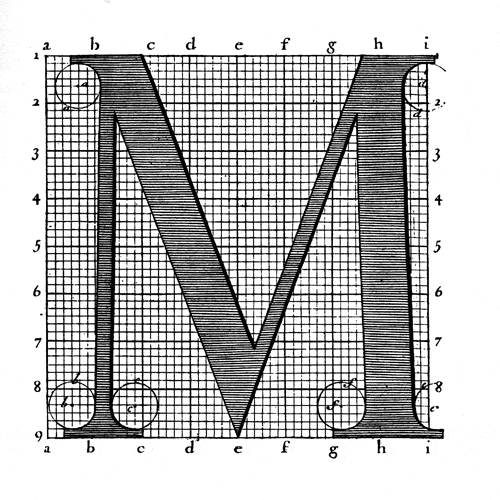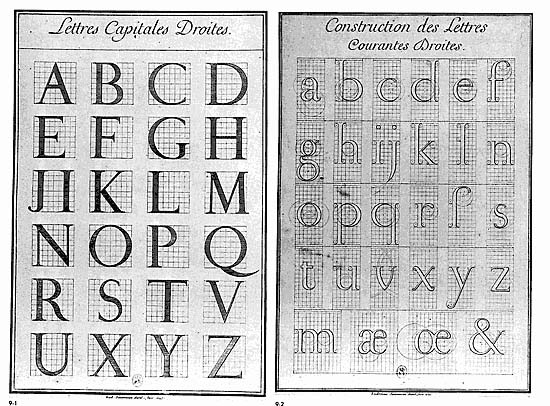
Grandjean / Roman du Roi
Os caracteres gravados por Grandjean romperam com a tradição dos caracteres criados por Jenson e Garamond e abriram caminho à construção de caracteres muito diferentes, nomeadamente aos criados por Didot e Bodoni, em que existe um contraste muito mais acentuado entre as hastes grossas e finas.
Grandjean
O Grandjean ou Romain du roi, do qual foram gravados 21 corpos entre 1693 et 1745. Foi o único tipo usado na 'Imprimerie Royale até 1811.
No século XVI, em plena Renascença, a melhor tipografia europeia vinha de França, mas já no fim do século a herança de Claude Garamond e Jannon entrou em declínio.
Para ressuscitar o esplendor francês, foi fundada em 1640 a 'Imprimerie Royale por decreto real.
No reinado do monarca absolutista Louis XIV, uma comissão real composta por dez especialistas investigou e debateu a partir do ano de 1692, até finalmente aprovar um tipo totalmente novo: o de Philippe Grandjean – em 1702.
Foram precisos dez longos anos para aprovar estes novos caracteres, baseados em conceitos matemáticos, construidos sobre uma grelha ortogonal. Este Grandjean, o «mais belo de todos os tipos», já não tinha qualquer afinidade com os padrões caligráficos que haviam cunhado as garaldes.
Depois de aprovado, o Grandjean passou a chamar-se Romain du Roi. Mas como o tipo era propriedade exclusiva da Imprimerie Royale, todas as outras fundições tiveram de fabricar os seus próprios tipos – o que acabou por favorecer a concorrência estrangeira.
Jean Anisson, director da Imprimerie Royale, tinha decidido renovar a Typographie royale. Tomou parte nas sessões da Commission Jaugeon, encarregada de definir o desenho dos caracteres.
Para executá-los, recorreu a Philippe Grandjean, gravador de punções e conservador da Fonderie Royale. Por sua vez, Grandjean recorreu aos serviços do seu aluno Jean Alexandre, (que lhe viria a suceder em 1723).
Mais tarde, Louis Luce, genro de Alexandre, completou a Grandjean do corpo 4, — Perle —, e um corpo de capitulares de 120 pontos.
Grandjean fez um trbalho original ao interpretar os desenhos da Commission - consultando mais os seus olhos — «juges souverains du goût» — que o compasso que Jaugeon e os seus associados tinham usado para conter os caracteres num quadrado que consistia de 2304 «pixels».
Concebido como uma arquitectura, a Roman du Roi separa-se nitidamente da caligrafia pela sua «juste proportion», pela sua regularidade e uniformidade.
Utilisation : « servir au plus magnifique ouvrage qui ait jamais paru » Par rapport au Garamont, le Grandjean apparaît comme réglé, avec ses empattements plus fins, presque sans transition avec les verticales qu'ils arrêtent.
As patilhas horizontais superiores obrigaram Grandjean à fazer a distinção do «l» minúsculo do «I» maisúsculo. Esta pequena particularidade passou a ser o sinal distintivo dos caracteres reais.
O Grandjean, ou Romain du roi, estava destinado a « servir au plus magnifique ouvrage qui ait jamais paru », as Médailles sur les principaux événements du règne de Louis le Grand (1702).